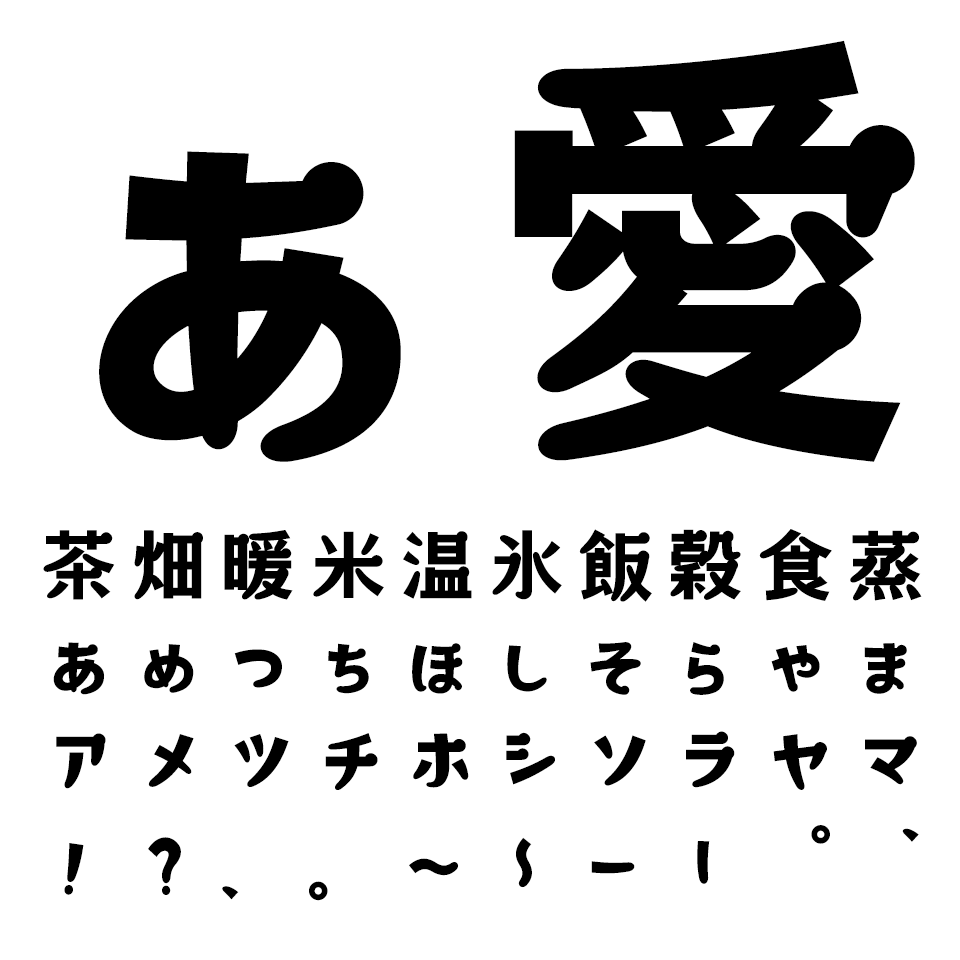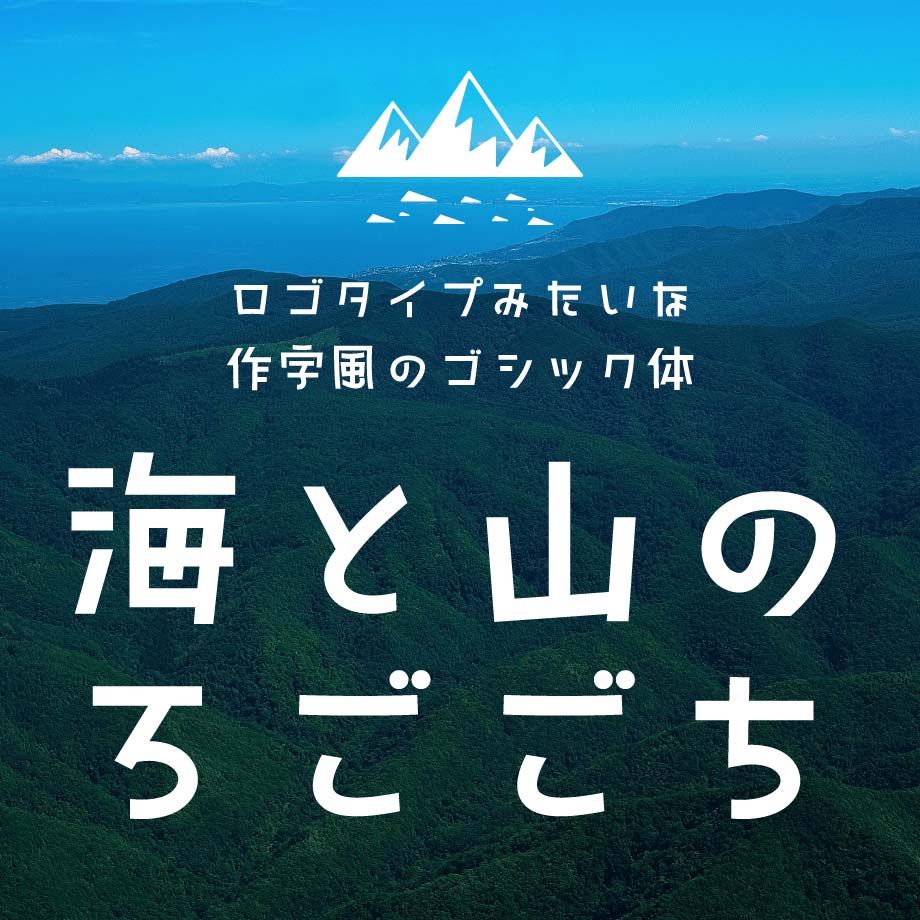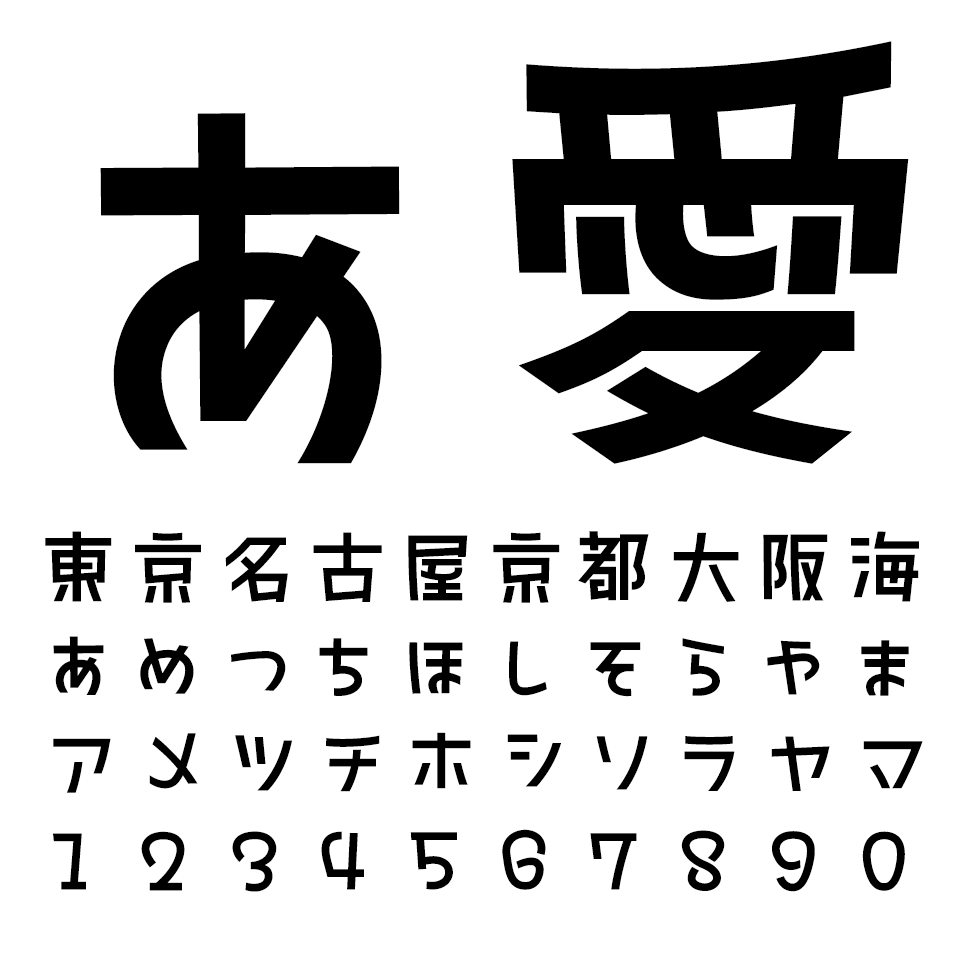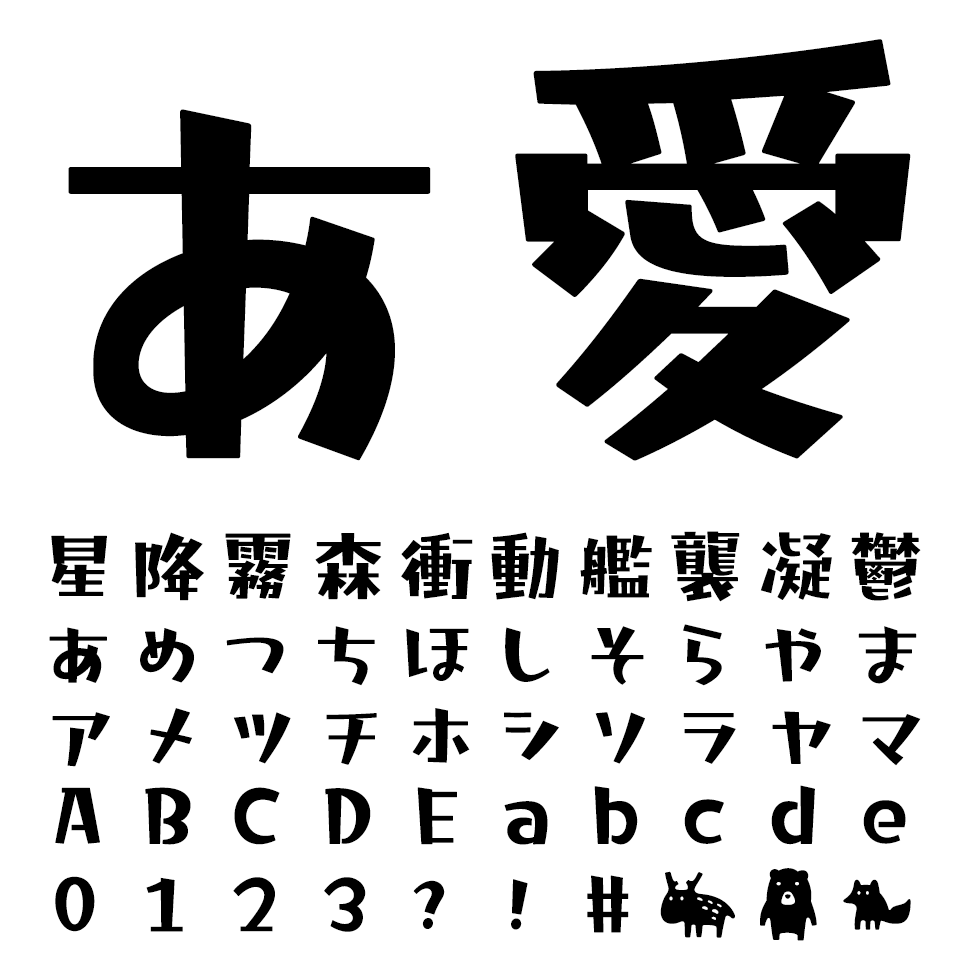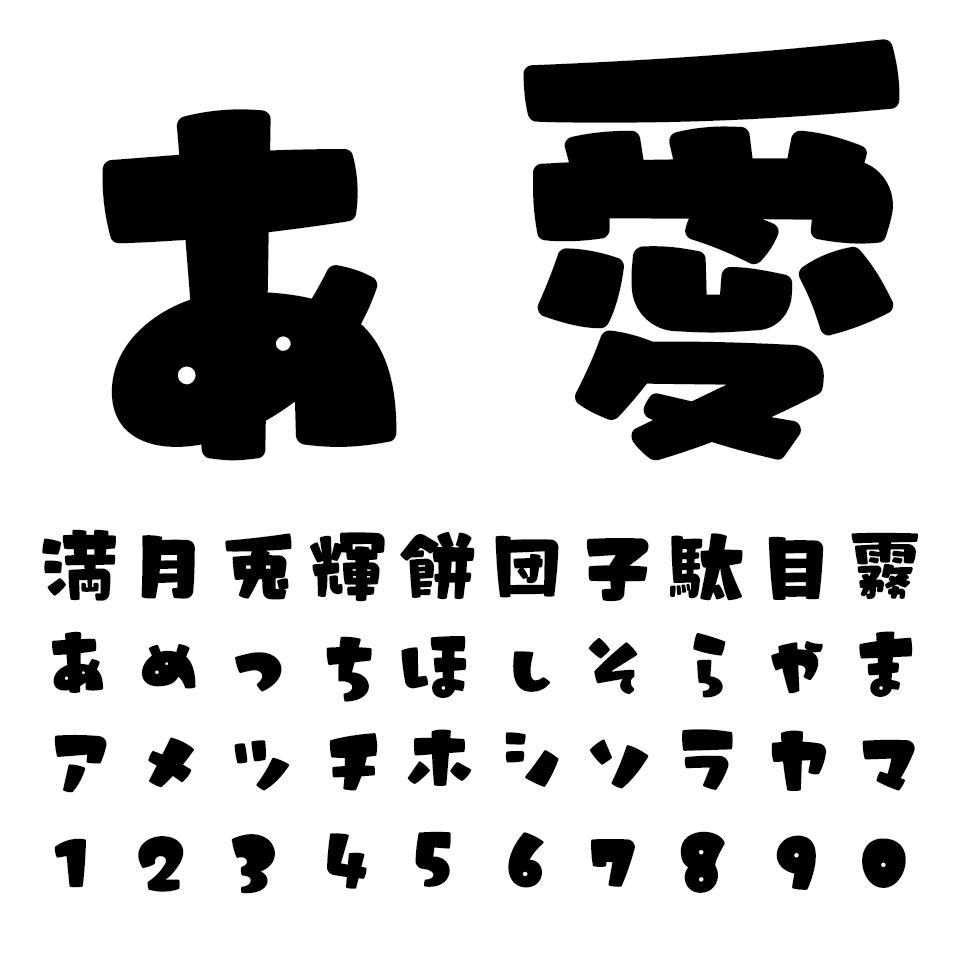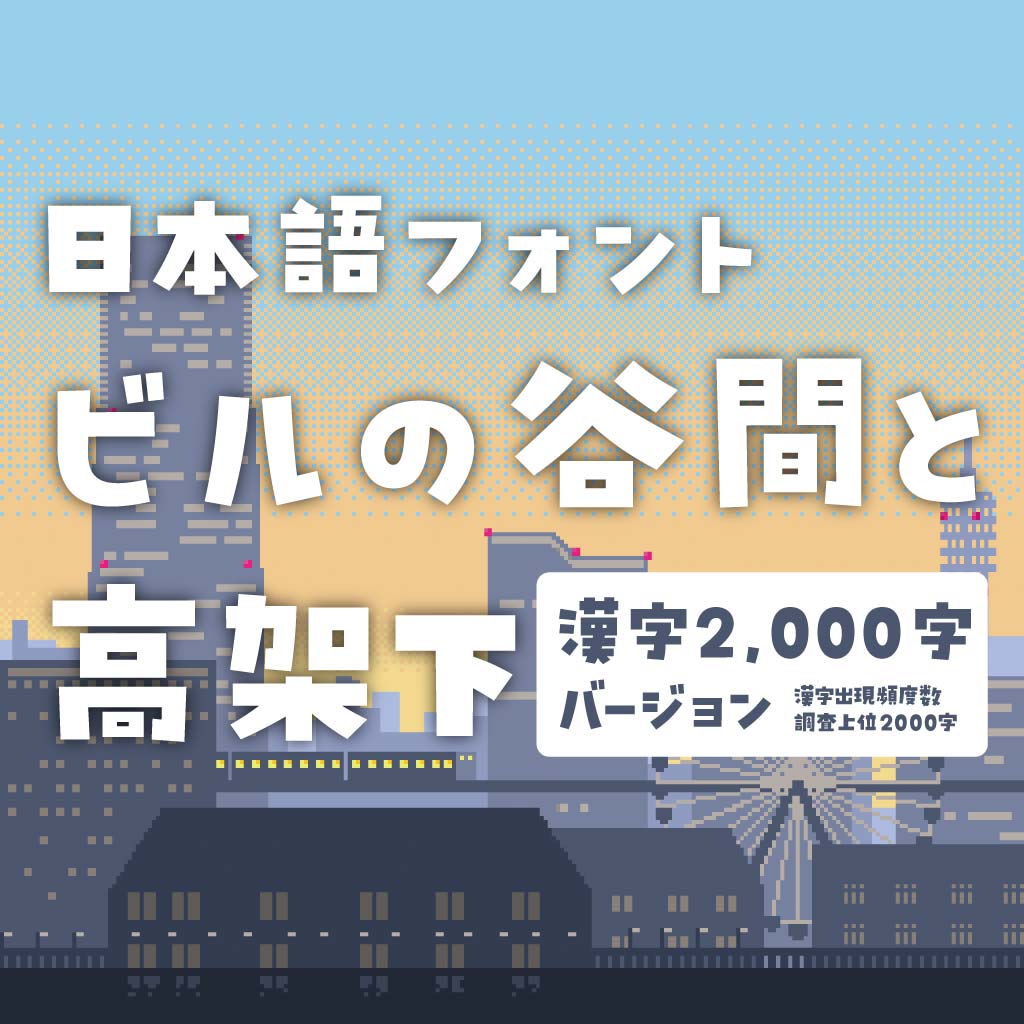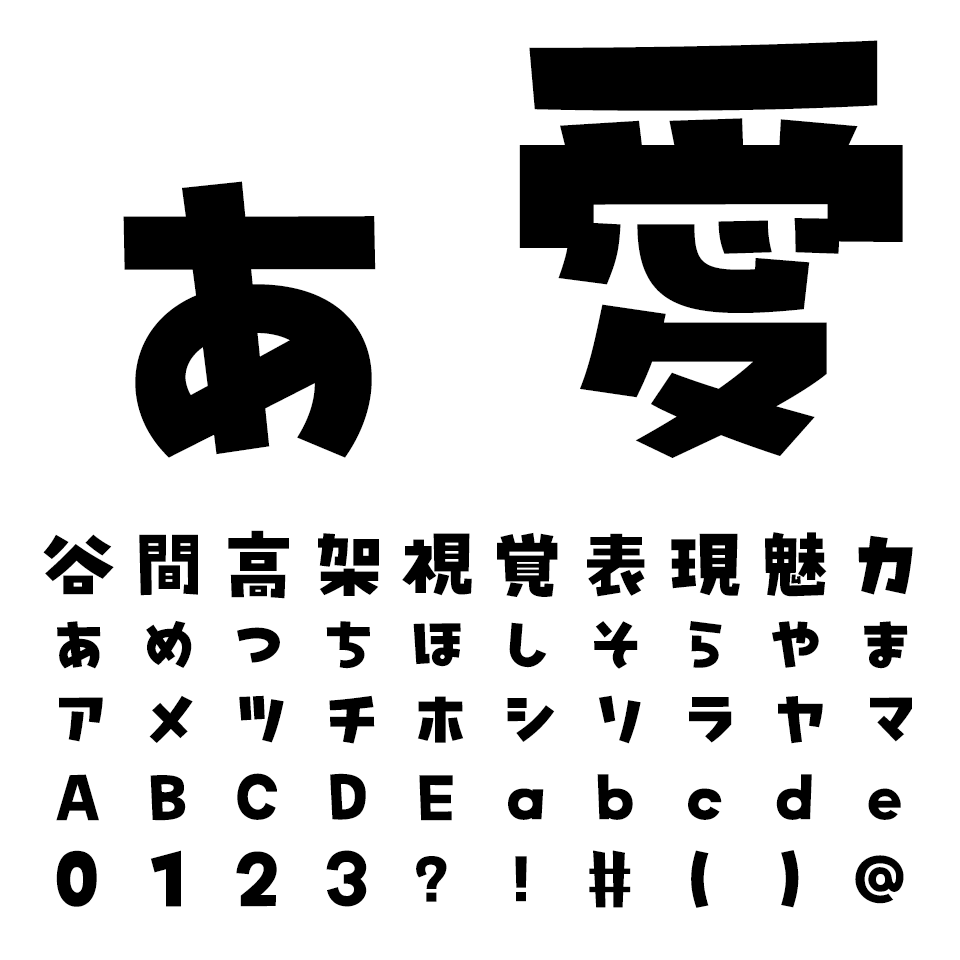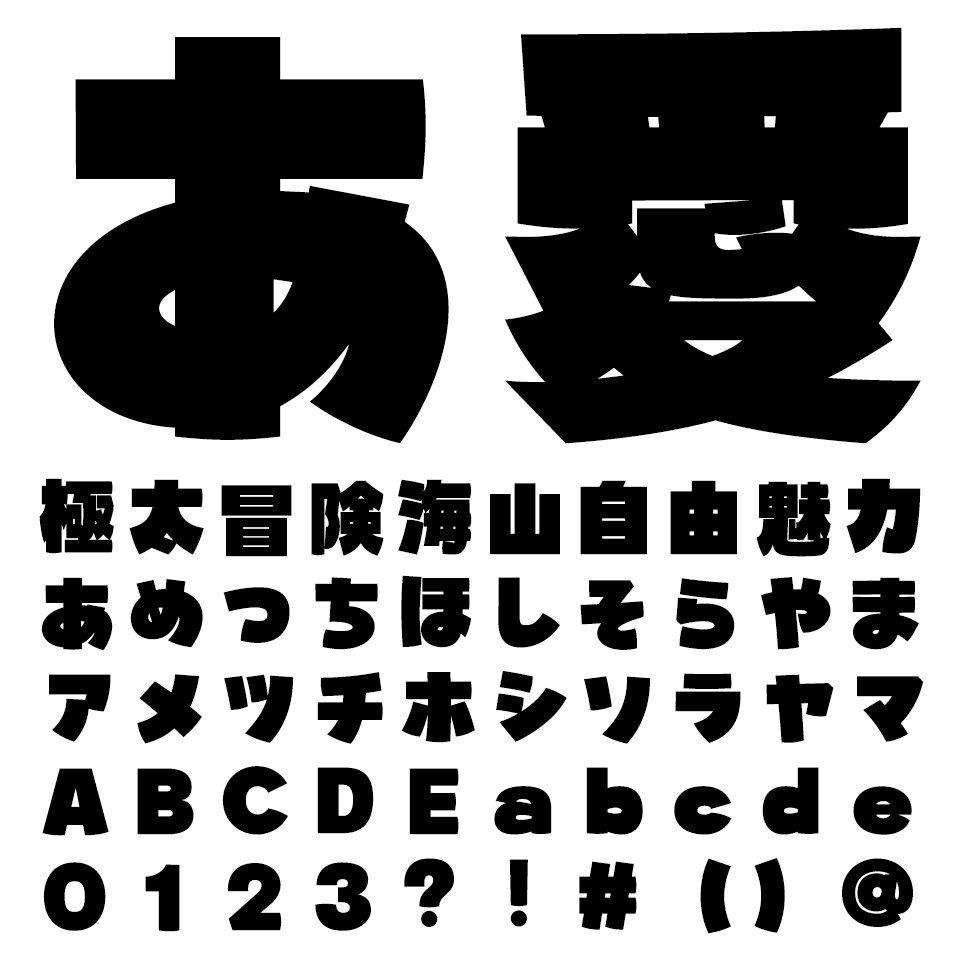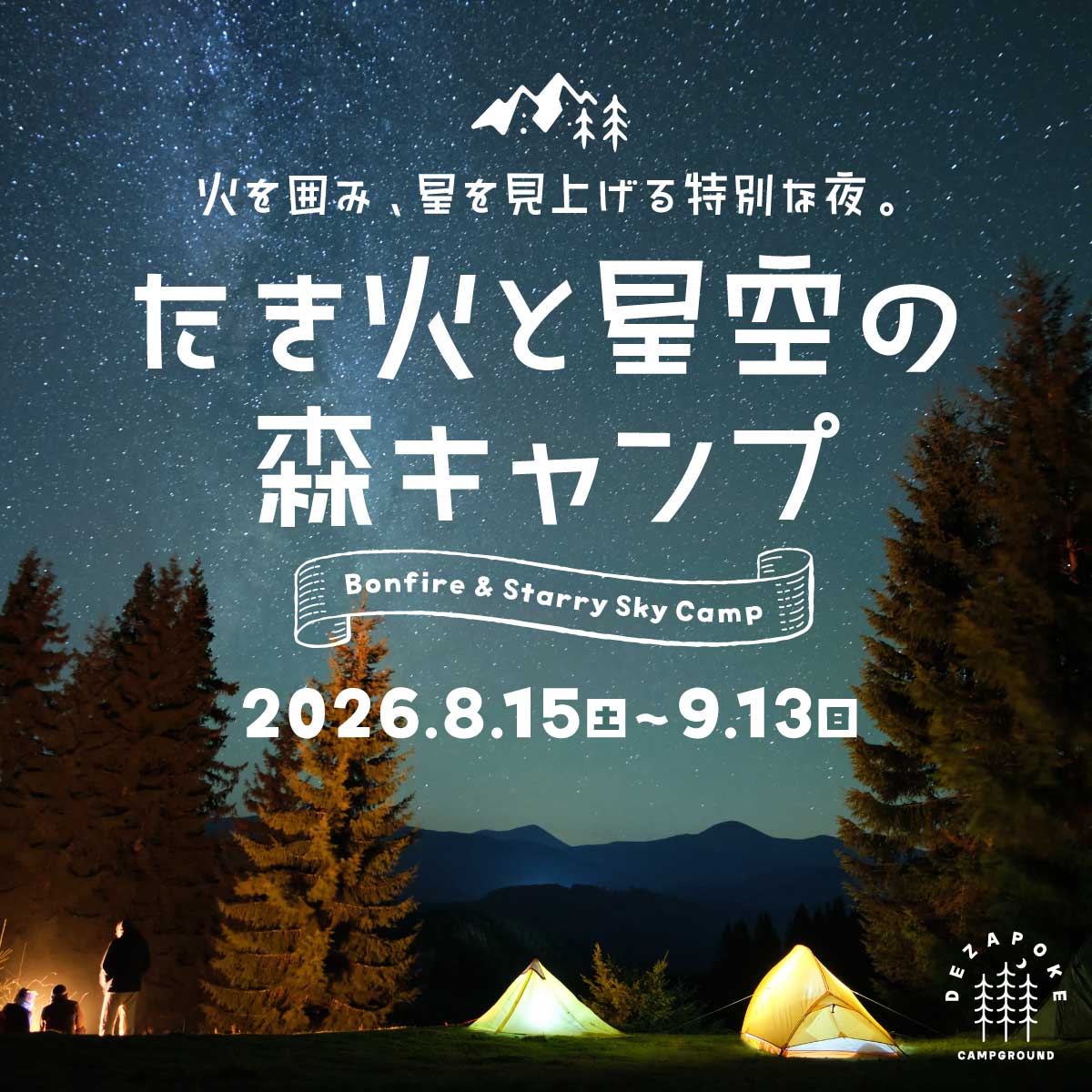
「文字で景色をつくる」をコンセプトに活動する元鉄道運転士がフォントデザイナーとして立ち上げたフォントブランド タイピングアート。文字が持つ空気感や物語を大切に、一つひとつの書体に個性と世界観を込めたフォントを制作しています。
丸明朝体、ゴシック体、サンセリフ体など、ロゴや短いコピー、SNS投稿、同人誌の表紙・タイトル、配信やサムネイルのサムネイルやテロップに使いやすい、使う人の表現に寄り添った個性的なデザイン書体が揃います。
森と湖の丸明朝
肉太で丸みのあるひらがなやカタカナが特徴の丸明朝体です。
漢字は教育漢字1,026文字を収録。英字・数字は収録していません。
海と山のろごごち
タイピングしただけで、作字風のロゴタイプが完成するフォントです。
漢字は教育漢字1,026文字を収録。英字・数字は収録していません。
藍と白のゆきぐに
縦画と横画、漢字の偏や旁にコントラストをつけ、重心が上部にあるフォントです。
漢字は常用漢字2,136文字を収録。英字・数字・一部記号も収録しています。
うさぎと満月のサンセリフ
二等身キャラクターのような愛嬌がある丸みを帯びたフォントです。
漢字は常用漢字までの2,136文字を収録。英字・数字・一部記号も収録しています。
ビルの谷間と高架下
文字を組んだ際に適度なデコボコ感が生まれる、親しみやすく愛らしいフォント。
漢字は文化庁の出現頻度数調査上位2,000文字を収録。英字・数字・一部記号も収録しています。
鳩とブリキのワンダランド
懐かしくレトロな趣ある情感。極太フォルムの存在感を極限まで表現したフォントです。
漢字は文化庁の出現頻度数調査上位2,000文字を収録。英字・数字・一部記号も収録しています。